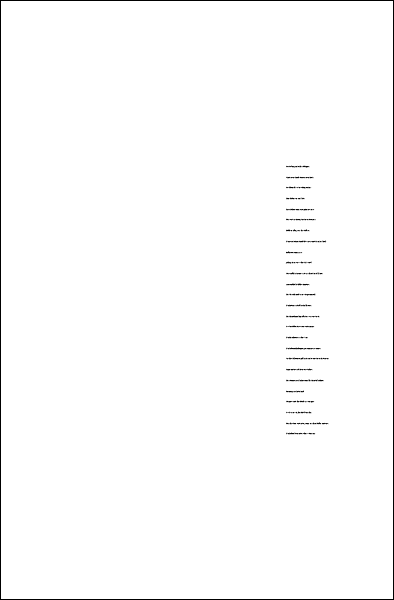
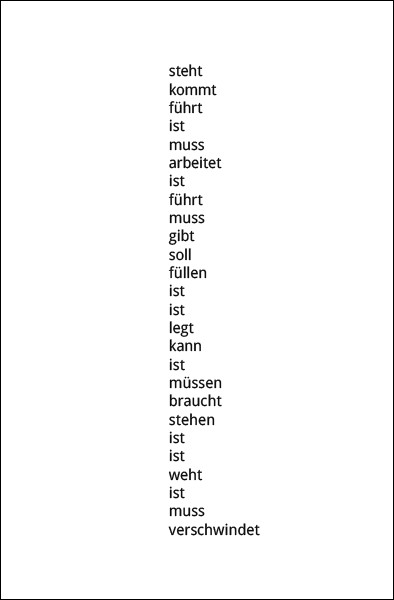
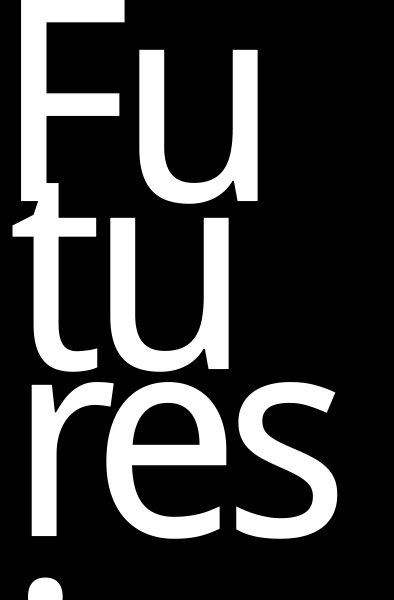
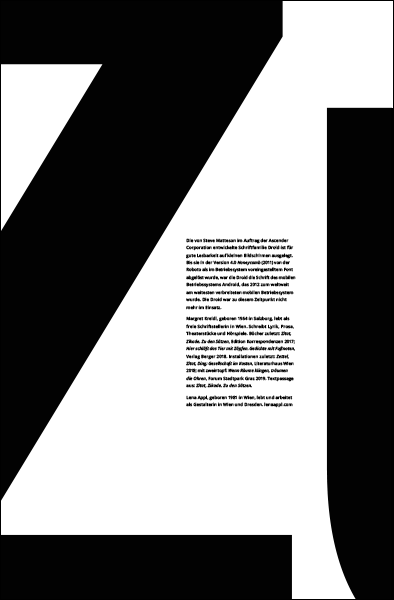
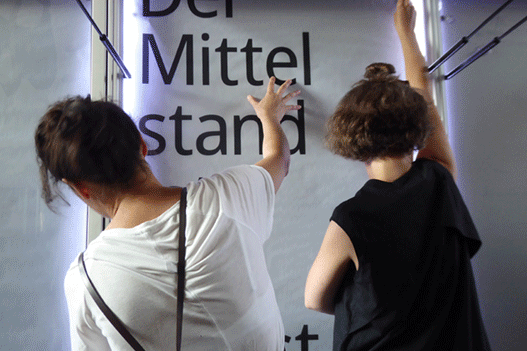
Text
Margret Kreidl, geboren 1964 in Salzburg, lebt als freie Schriftstellerin in Wien. Schreibt Lyrik, Prosa, Theaterstücke und Hörspiele. Bücher zuletzt: Zitat, Zikade. Zu den Sätzen, Edition Korrespondenzen 2017; Hier schläft das Tier mit Zöpfen. Gedichte mit Fußnoten, Verlag Berger 2018. Installationen zuletzt: Zettel, Zitat, Ding: Gesellschaft im Kasten, Literaturhaus Wien 2018; mit zweintopf: Wenn Räume klingen, träumen die Ohren, Forum Stadtpark Graz 2019. Textpassage aus: Zitat, Zikade. Zu den Sätzen.
Typografie
Die von Steve Matteson im Auftrag der Ascender Corporation entwickelte Schriftfamilie Droid ist für gute Lesbarkeit auf kleinen Bildschirmen ausgelegt. Bis sie in der Version 4.0 Honeycomb (2011) von der Roboto als im Betriebssystem voreingestelltem Font abgelöst wurde, war die Droid die Schrift des mobilen Betriebssystems Android, das 2012 zum weltweit am weitesten verbreiteten mobilen Betriebssystem wurde. Die Droid war zu diesemZeitpunkt nicht mehr im Einsatz.
Gestaltung